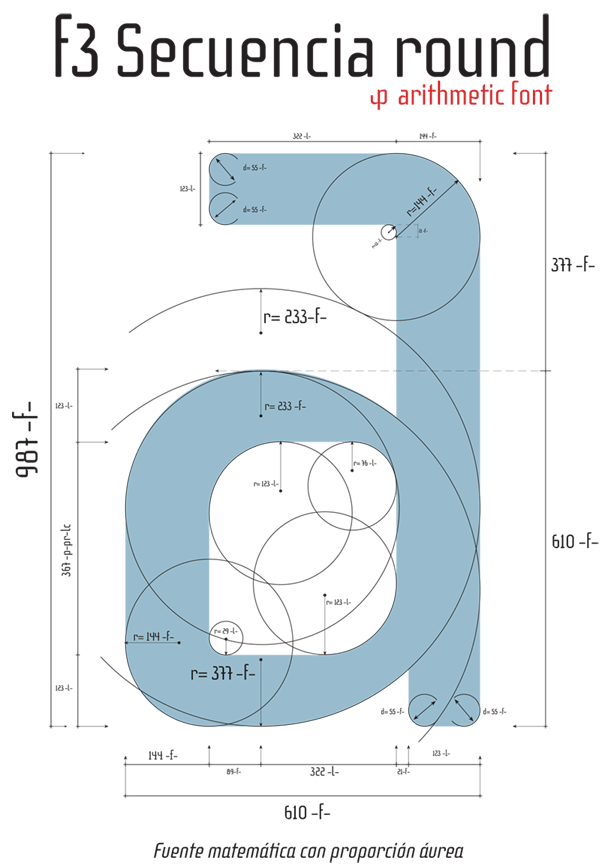
Esta es la tercera fuente correspondiente a la serie de fórmulas constructivas con proporciones áureas en versiones regular, negrita, itálica y Negrita Itálica. En este caso esta tipografía comparte con la primera de la serie f1 Secuencia Quad sus proporciones generales de altura y anchura de letras, en este caso sólo varío con respecto a la primera los ángulos de las esquinas con otras cifras de la secuencias matemáticas resultando una versión redondeada de esta fuente geométrica especialmente preparada para textos de párrafo y títulos en diseño editorial.
Fuente con proporción áurea
Estilo: Sans, Rounded, Geometric
Proporción: Regular, Bold & Italics
Glyphs: 609
Funciones OpenType: Additional languages, Denominators, Discretionary Ligatures, Extended Fractions, Inferiors, Kerning, Mathematical Greek, Numbers Small Caps, Numerators, Oldstyle Figures, Ordinals, Scientific Inferiors, Standard Ligatures, Subscript, Superiors, Superscript.
El uso práctico de esta fórmula se puede ver en el póster constructivo de la letra ‘a’ minúscula, observar las proporciones que inscriben la letra, 987×610 pt, dos números correlativos de la sucesión de Fibonacci que conforman lo que se llama un rectángulo áureo.Toda la definición de espacio entre caracteres y kerning así como como el espaciado de palabras (Tracking) está definido con números de las siguientes secuencias matemáticas.
Fibonacci: 0, 1, 2, 3, 5, 8, 13, 21, 34, 55, 89, 144, 233, 377, 610, 987, 1597…
Lucas: 2, 1, 3, 4, 7, 11, 18, 29, 47, 76, 123, 199, 322, 521, 843, 1364, 2207…
Tribonacci: 1, 2, 4, 7, 13, 24, 44, 81, 149, 274, 504, 927, 1705, 3136…
La tipografía f3 Secuencia round en su versión comercial dispone de un juego de caracteres de 609 caracteres (Latin-Extended Character) con soporte para cualquier idioma europeo o centro europeo y el alfabeto griego, también contiene funciones Open Type y letras con formas alternativas, Aa, Bb, c, d, e, g, m, n, o, Pp,Qq, R, S, u, el símbolo et (Y comercial o ampersand) y la arroba. La versión comercial Incluye fuentes para la web (webfonts).